最近易烊千玺的签名火了,也是有很多人开始模仿着易烊千玺的签名体,开始设计自己的签名。有一些人还开始在网上寻求易烊千玺签名字体的教程。那像易烊千玺艺术字体签名是如何设计的呢?
“易烊千玺”签名字体火了,这些艺术字体签名还远吗?
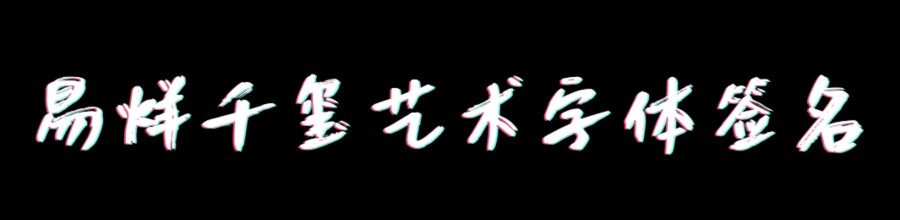
易烊千玺艺术字体签名如何设计?
不就是要讲自己的名字写出来,不过写的时候需要用两支笔握在一起的方式进行些,这样就会出现两层字体。在写的时候最好是用一个颜色比较深的,一个颜色相对比较浅的来写。 这名字写好之后,就要用铅笔将上下两面字体连接在一起,然后制造出阴影的感觉,这样写出来的字就相对来说具有立体感,非常简单,但是效果却不一样。连接好了以后,接下来就是比较重要的啦,就是要用棉签将刚刚做好了的底线晕染一下。
通过上面这些方法将自己的名字设置成了易烊千玺艺术字体签名后,整个感觉会更加立体,而且比较逼真。最后就是将海水比江下边的描好的线加重一遍就可以了,这样效果就不会那么假,最后最终效果已经呈现。